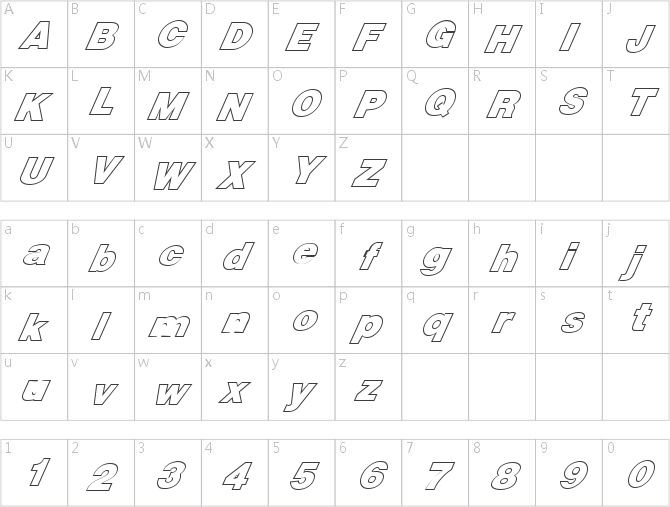
FZ BASIC 13 HOLLOW ITALIC 詳情頁
FZ BASIC 13 HOLLOW ITALIC字體字庫是一款讓人賞心悅目、百看不厭的英文字體,適合各類廣告和產(chǎn)品包裝設(shè)計(jì)應(yīng)用,字體大小0.07MB,格式為ttf字體,上傳用戶是得·岸,作者/版權(quán)方為未知